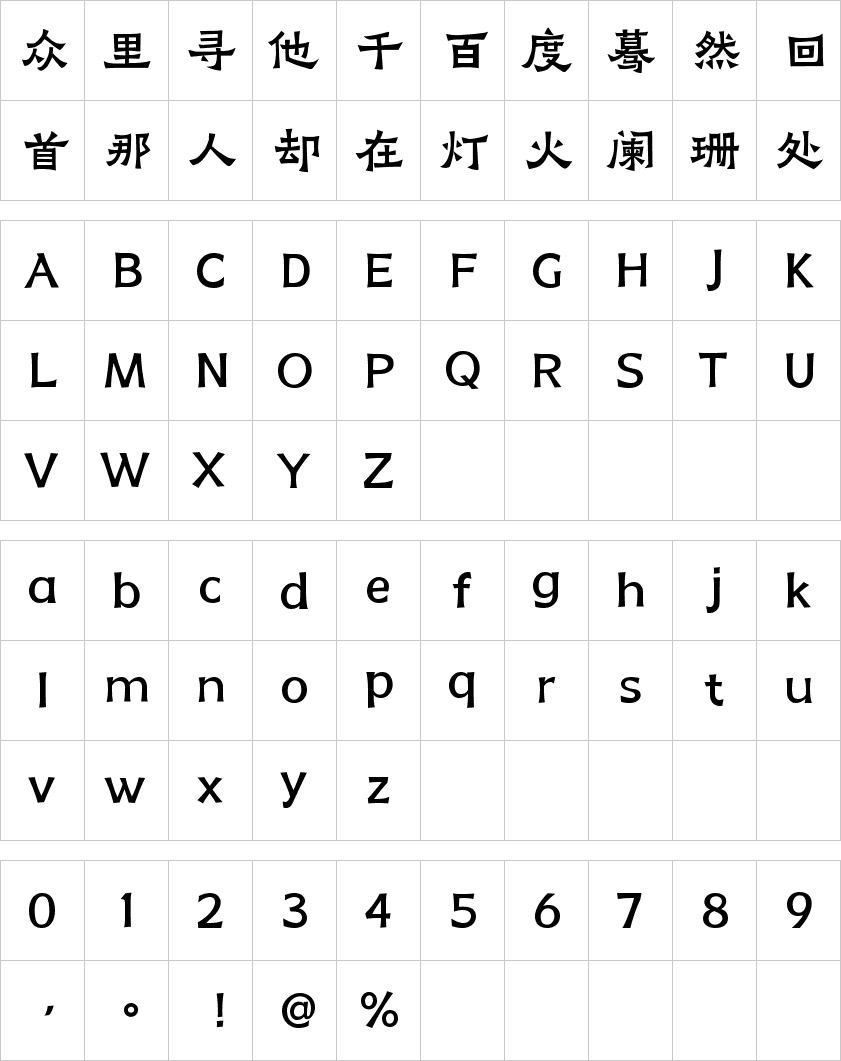
阿里妈妈刀隶体
阿里妈妈刀隶体为中文简体字库,收纳的中文字符包括但不限于GB2312,共计6763个汉字;英文大小写共52个;常用标点符号共227个,总计7042个字符
设计说明:阿里妈妈刀隶体,通过机器学习了爨宝子碑的精髓,强调了三角点折弯与横画两端“雁尾”之方强,外露锋芒,耀其精神,介于隶楷之间,保持着浓重的隶书方笔意味,给人以坚实、朴茂、稚拙、倔犟之感,打破常规常态的匀称均衡,结字极为大胆,大小常常出人意料,看似失度,实则深得艺理,险中求正,静中寓动,动中求静。